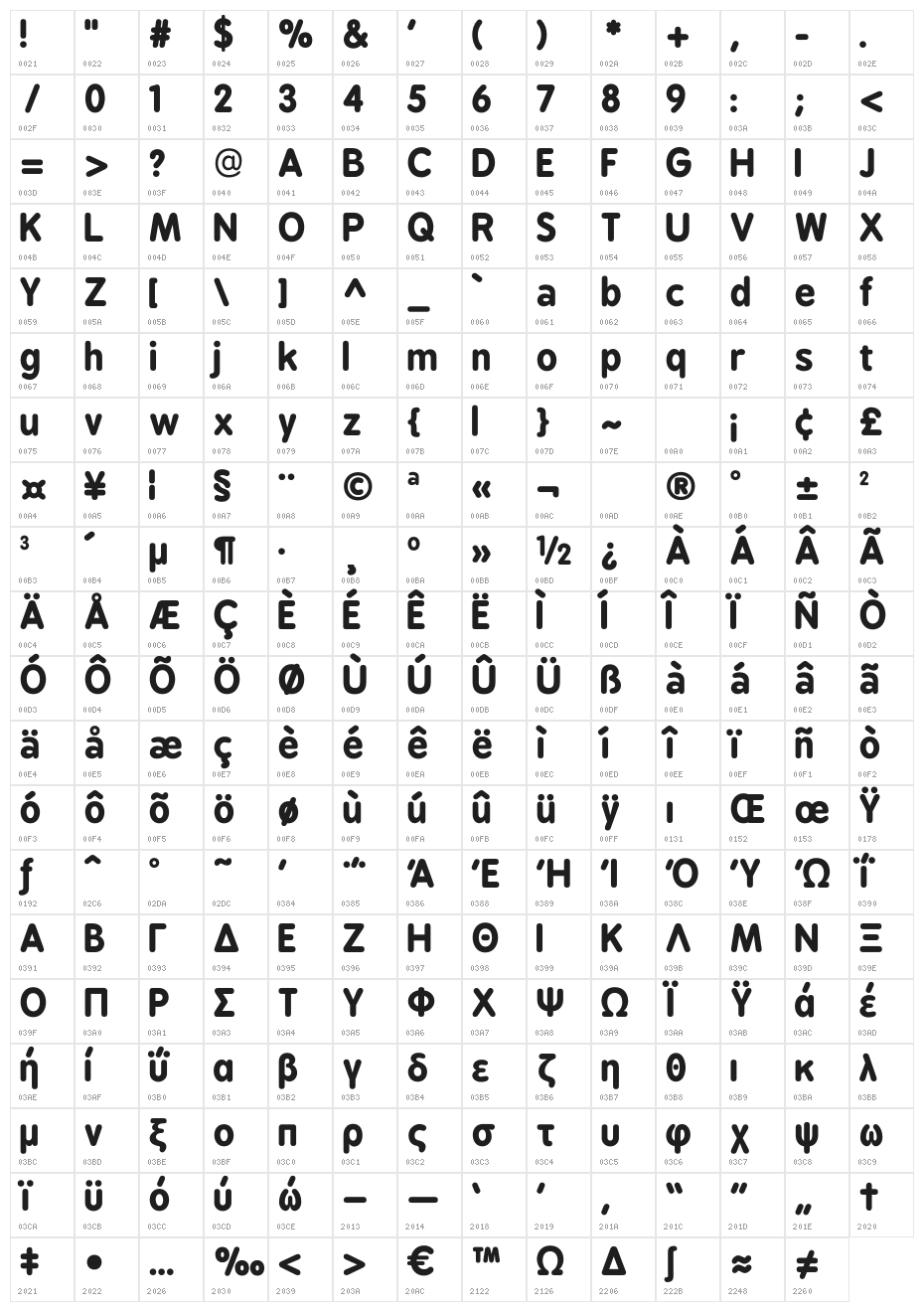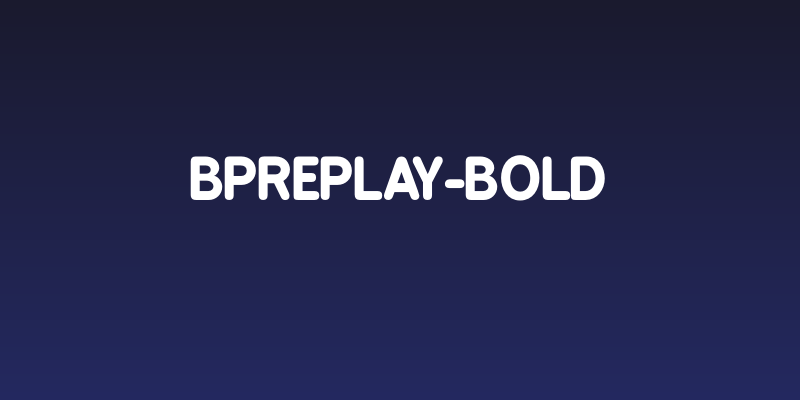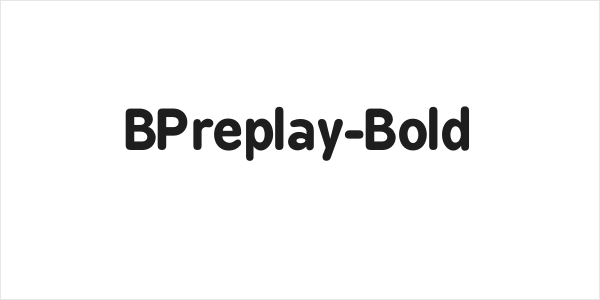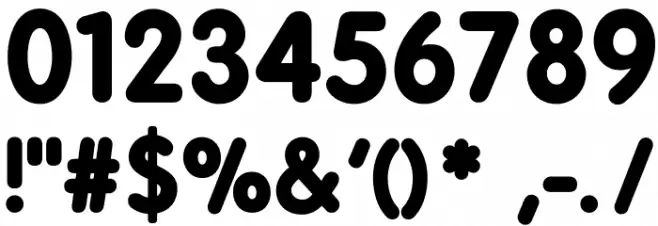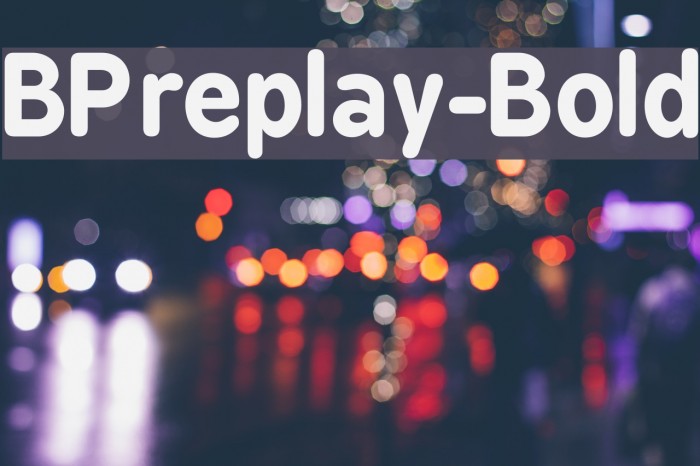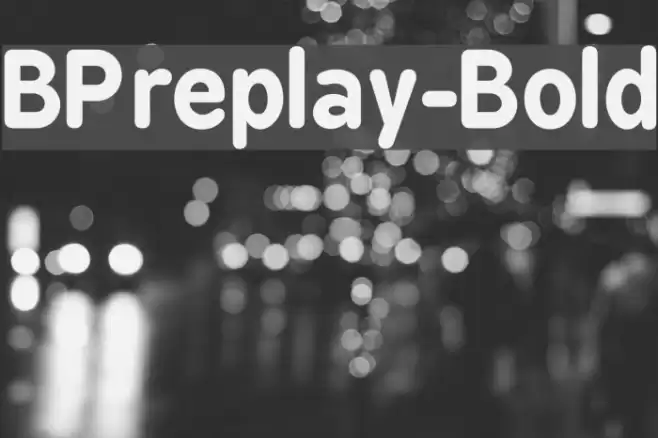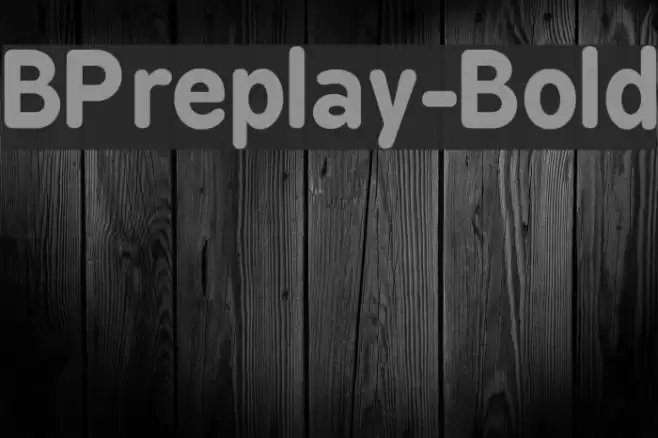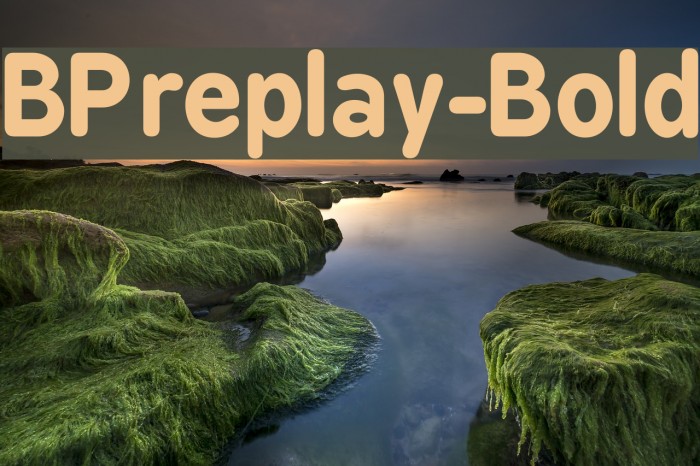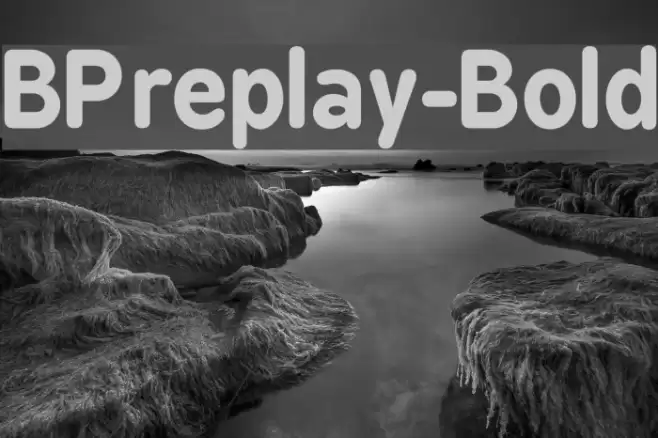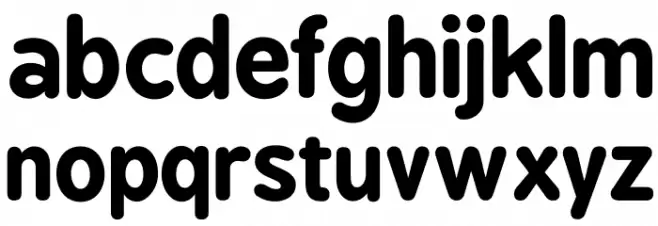
BPreplay-Bold Font
✎ Sans Serif
| Proyectos propuestos | Ideal for branding, headlines, posters, and digital media where a bold and approachable look is desired. |